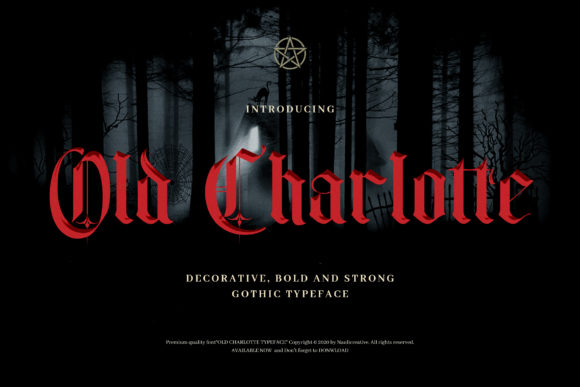
Old Charlotte
Old Charlotte : la font blackletter incontournable pour vos projets créatifs
Si vous cherchez une font qui allie élégance et authenticité, Old Charlotte est exactement ce qu’il faut. Cette typographie blackletter séduit par ses traits classiques et ses courbes raffinées, idéale pour donner du caractère à vos idées créatives. Intégrez Old Charlotte dès aujourd’hui et observez comment vos designs prennent vie avec une touche d’histoire et de modernité.
- Une esthétique blackletter qui évoque le passé tout en restant actuelle.
- Polyvalence exceptionnelle : affiches, logos, titres web, invitations et plus encore.
En résumé, Old Charlotte est le choix parfait pour les créateurs qui veulent ajouter une touche authentique et professionnelle à leurs réalisations. Ne manquez pas l’opportunité d’enrichir votre palette typographique avec cette police unique en son genre.